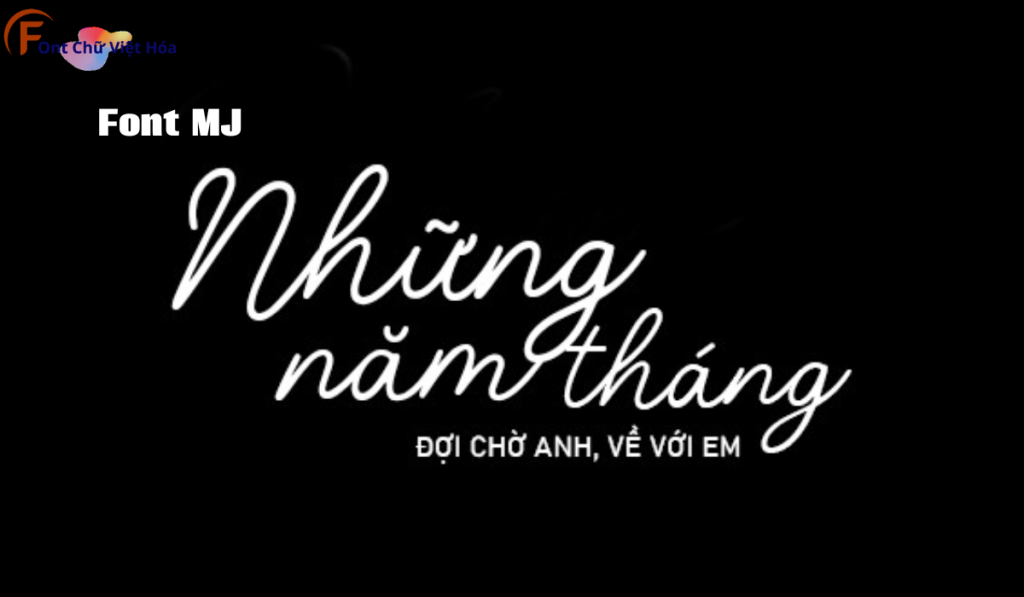
Font MJ Halitage Script Việt Hóa
Tác giả: MJ
Bộ Font: MJ
Kiểu chữ: Chữ viết tay
Font MJ Halitage Script Việt Hóa là một font chữ viết tay cá tính, thuộc bộ font MJ. Được thiết kế với mục tiêu mang lại sự mềm mại và thanh thoát, font này lý tưởng cho các dự án thiết kế như thiệp mời, logo, và bao bì sản phẩm. Với các nét chữ uyển chuyển và độ dày đều đặn, Font MJ Halitage Script Việt Hóa không chỉ dễ đọc mà còn tạo cảm giác thân thiện và gần gũi. Việc Việt hóa font giúp người dùng dễ dàng sử dụng trong các thiết kế tiếng Việt, mang lại sự tiện lợi và thẩm mỹ cao.